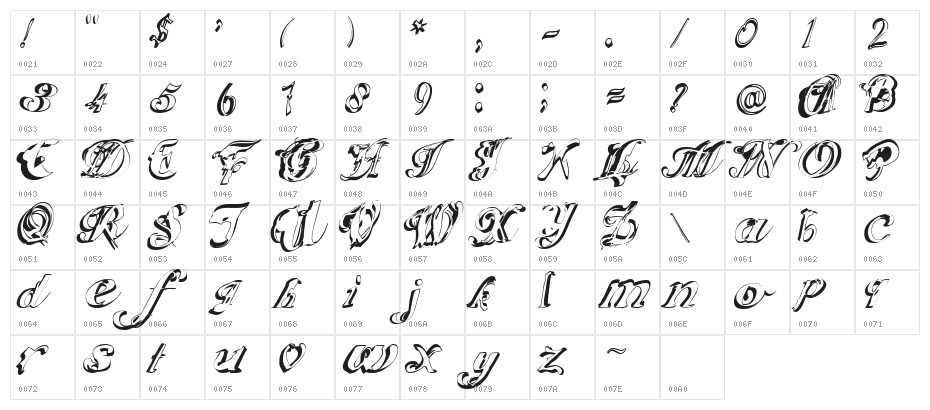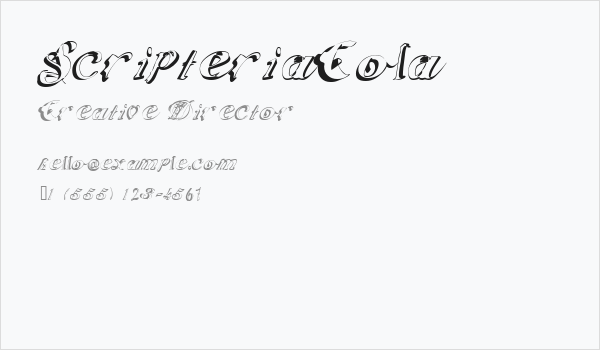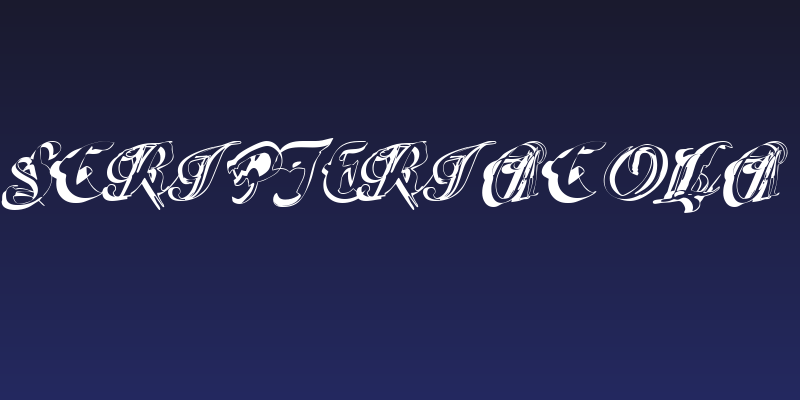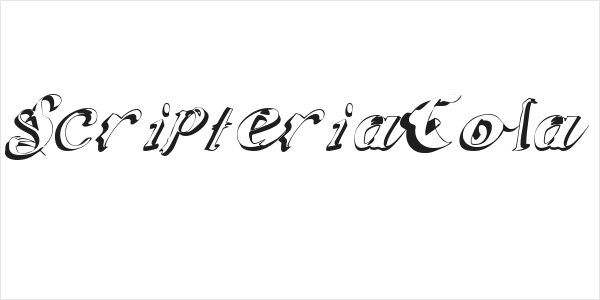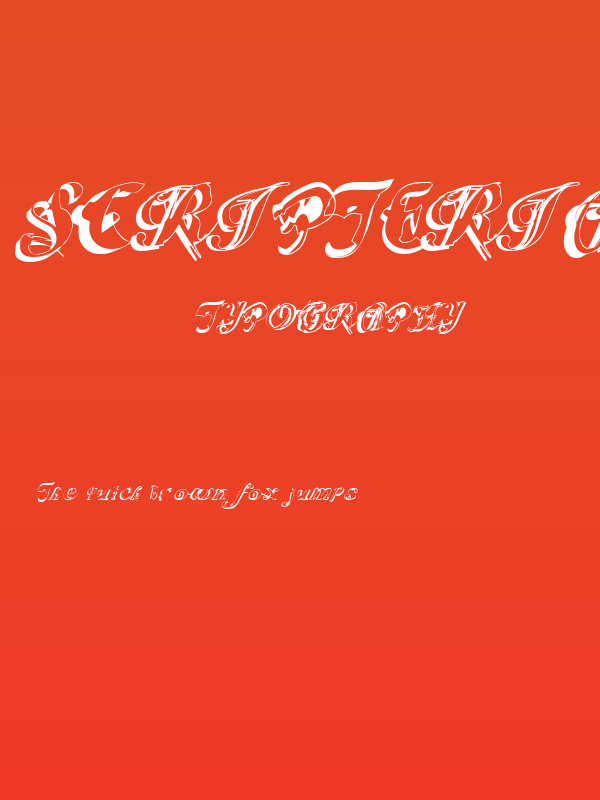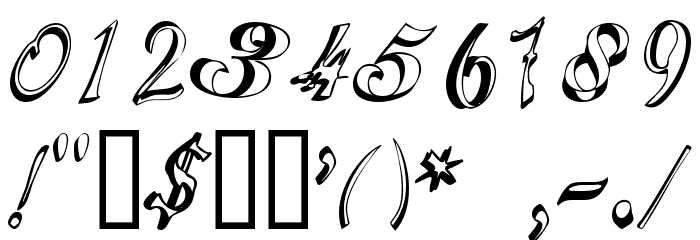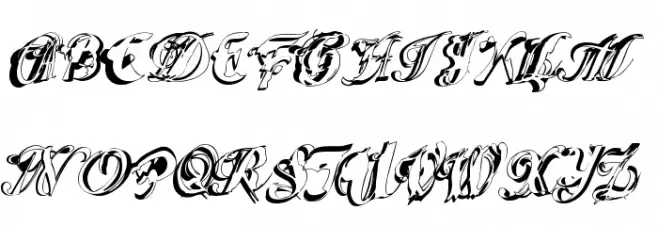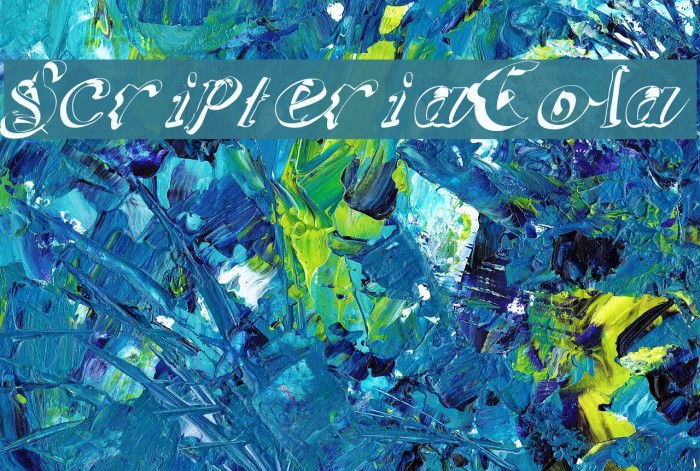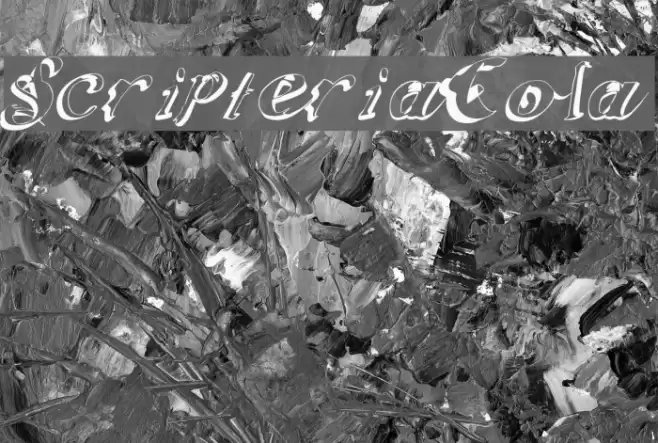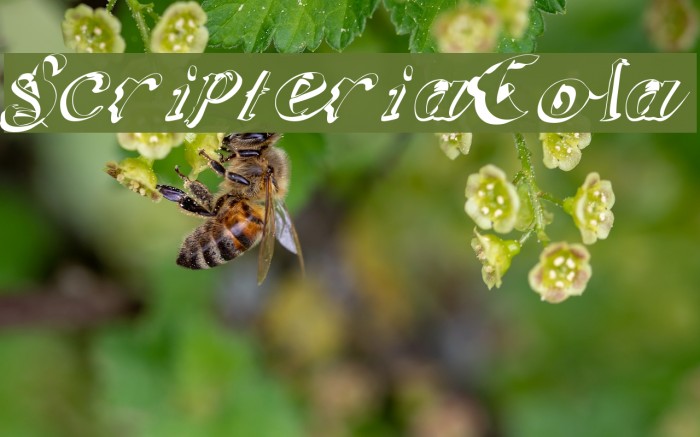
ScripteriaCola Font
| Cas d'utilisation | Headlines, Logos, Invitations |
| Projets proposés | Ideal for wedding invitations, luxury branding, artistic posters, and decorative headlines. |